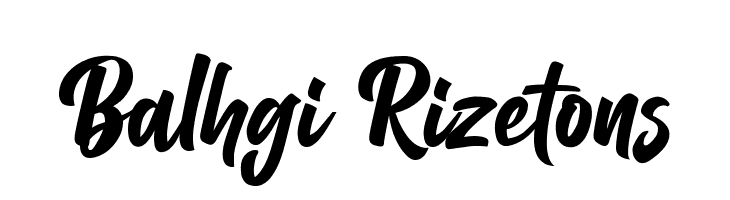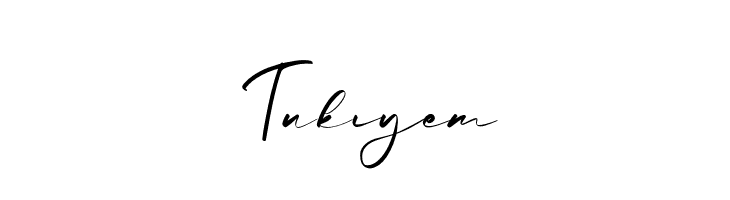
每款 新字体 都有独特个性:从干净现代的无衬线到富有表现力的手写体、醒目的展示体。 我们频繁更新列表,你可以先在线预览再免费下载使用。
A playful, casual handwritten font with tall, narrow letters and rounded edges.
A playful and energetic handwritten font with dynamic strokes.
A playful handwritten font with thin, fluid strokes and a whimsical style.
A lively and expressive handwritten font with dynamic strokes and playful elegance.
A lively, handwritten font with dynamic strokes and a playful aesthetic.
An elegant, cursive font with flowing, handwritten style and ornate flourishes.
A playful, cursive script font with flowing, connected letterforms.
A modern, elegant script font with a flowing, handwritten style.
A playful and elegant handwritten font with fluid strokes and artistic flair.
A playful, casual handwritten font with dynamic strokes.